타이포브랜딩 : 대표적 성공사례
수십 년, 또는 그 이상을 성공적인 브랜드로 자리매김하고 있는 기업들의 커뮤니케이션 활동에서 주목해야 할 것도 바로 그 브랜드만의 전용서체입니다. 이번에는 국내외 유수의 기업들과 산돌커뮤니케이션이 함께 진행한 타이포브랜딩 성공사례들을 살펴보도록 하겠습니다.
타이포브랜딩 : 대표적인 전용서체 성공사례
타이포브랜딩은 타입(서체)을 통한 기업의 차별화된 브랜딩 활동을 의미합니다. 이번에는 국내외 유수의 기업들과 산돌커뮤니케이션이 함께 진행한 타이포브랜딩의 대표적인 성공사례들을 살펴보도록 하겠습니다.
Apple SD Gothic Neo / 애플 X 산돌커뮤니케이션
애플은 아이폰의 iOS 5부터 기본 글꼴로 산돌고딕네오1을 채택하여 사용하고 있습니다. 이는 산돌고딕네오1이 자사의 디자인 아이덴티티와 가장 잘 어울리며, 심미성 및 가독성이 뛰어나다고 판단했기 때문입니다.
이후부터 전세계로 판매되는 모든 애플 디바이스에는 산돌고딕네오1이 한글을 대표하는 기본 폰트로 탑재되고 있으며, 이를 통해 가독성이 개선되어 한글의 아름다운 디테일을 보다 잘 느낄 수 있게 되었습니다. 또한 한글을 사용하는 이용자들의 만족도도 크게 높아진 것도 사실입니다.
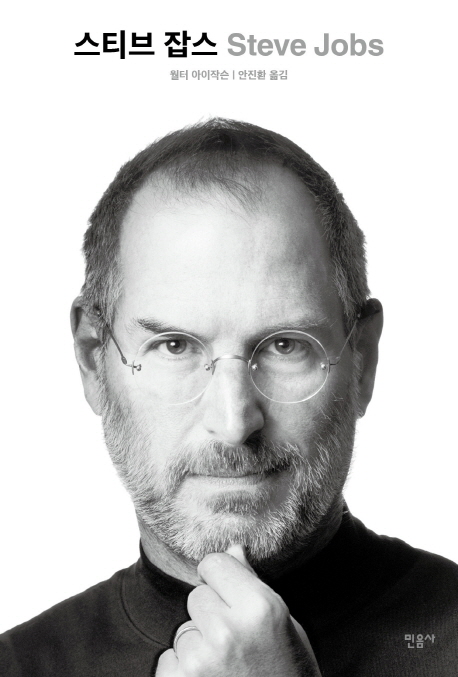
산돌고딕네오1이 적용된 스티브 잡스 자서전
본고딕(Source Han Sans) / 구글 X 어도비 X 산돌커뮤니케이션
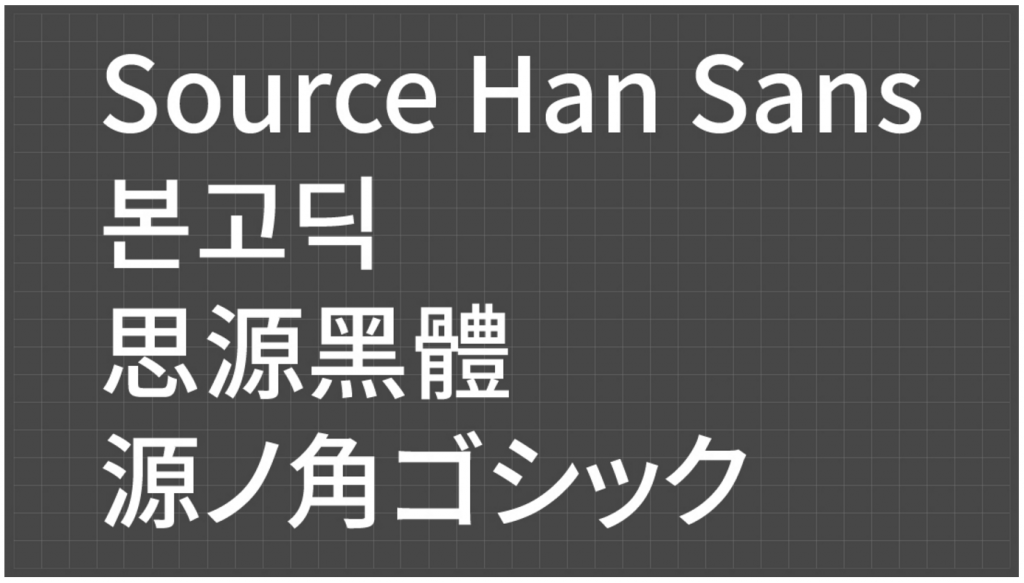
최초의 오픈소스 한중일 통합폰트, 본고딕
구글과 어도비 그리고 산돌이 협력하여 한중일 3개 국어와 라틴어를 모두 지원하는 슈퍼 폰트가 만들어졌습니다. 바로 본고딕 or 노토 산스 CJK(Noto Sans CJK)입니다. 어도비는 ‘누구나 사용 가능한 오픈 소스 서체 개발’에 지속적으로 관심을 가지고 있었고, 구글 역시 같은 뜻으로 프로젝트에 함께 했습니다. 전세계 모든 정보를 체계화해 언제 어디서 누구든 용이하게 정보에 접근하게 하는 것이 구글의 목표이기 때문입니다. 한글은 다양한 글로벌 프로젝트 경험을 보유한 산돌이 담당하였습니다.
한중일 3개국어를 완벽하게 지원하는 7종류의 굵기로 제작되었으며, 각 나라 글꼴의 특색을 살리면서도 조화롭고 일관된 느낌을 받을 수 있도록 제작하였습니다. 전체적으로 세련되고 현대적 스타일의 고딕체로 간소하고 일관된 획 두께로 표현되었으며 스마트폰 및 태블릿 같은 작은 화면의 디바이스에서도 텍스트를 보다 쉽게 읽을 수 있도록 가독성을 고려했습니다. 본고딕은 오픈소스이기 때문에 컨텐츠 제작자나 개발자, 디자이너들이 마음껏 사용할 수 있습니다. 이를 통해 보다 원활한 작업을 돕고 한층 향상된 사용자 경험을 제공할 수 있게 되었습니다.
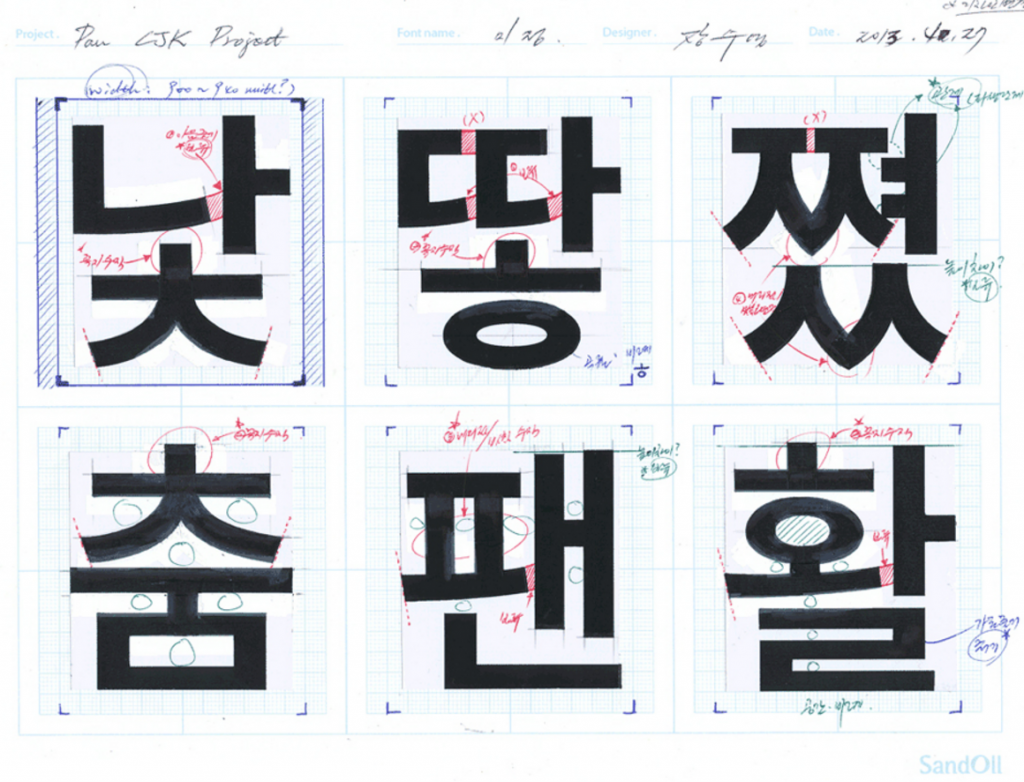
본고딕의 원도 스케치 자료
맑은고딕 / Microsoft X 산돌커뮤니케이션
모니터에 최적화된 최초의 한글 폰트, 맑은고딕
Microsoft는 Windows Vista 출시와 함께 고해상도 디스플레이 기기의 보급에 맞춰 비-라틴 언어권의 기본 폰트를 대폭 개선하기로 하였습니다. 맑은 고딕은 그 일환으로서 기존에 굴림체가 차지하고 있던 기본 UI 글꼴을 Windows Vista에서부터 대체하였습니다.
이를 위해 산돌 석금호 대표가 마이크로소프트 미국 본사를 찾아가 3일동안 경영진 및 실무자들과 차례로 토론을 벌여 설득했다는 일화는 유명합니다. 이후 2년에 걸쳐 15명의 디자이너가 개발에 투입됐으며, 마이크로소프트 본사의 엄격한 품질 검사를 모두 통과하고 2004년 Windows Vista에 탑재된 것입니다. 한글에 매뉴얼 힌팅이 적용된 최초 사례로 모니터에 최적화된 최초의 한글 폰트라 할 수 있으며, 이를 통해 화면 상에서 조형성 및 가독성을 극대화 시킬 수 있었습니다.
나눔고딕 by 네이버 X 산돌커뮤니케이션
나눔고딕은 네이버가 진행하는 ‘한글한글 아름답게’ 캠페인의 일환으로 나눔글꼴 시리즈 중 가장 먼저 출시되었습니다. 기존 굴림체에 현대적인 감각을 적용한 새로운 느낌의 고딕체로 부드러운 인상이 특징입니다.
모양도 깔끔하고 가독성도 좋아서 많은 사람들의 사랑을 받고 있는 국민폰트이기도 합니다. 네이버의 기본 폰트는 물론, 안드로이드나 우분투, 크롬 OS 등의 기본 한글폰트로 채택될만큼 사용성을 인정받았으며 칸 국제광고제에서 실버라이온스상을 수상할만큼 타이포브랜딩을 통한 마케팅 효과를 톡톡히 거두었습니다.
유앤아이(Youandi) / 현대카드 X 산돌커뮤니케이션
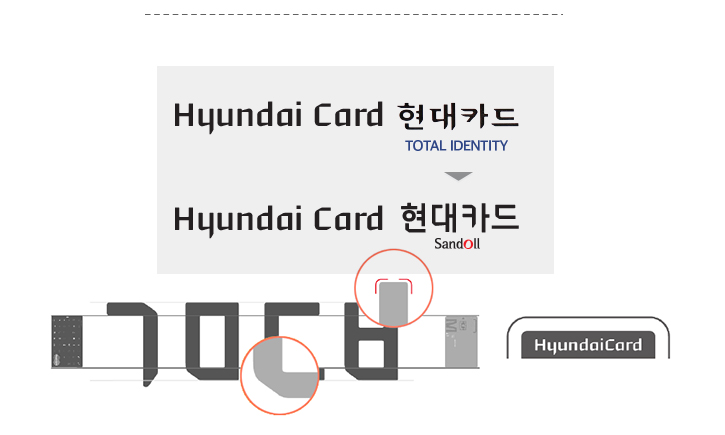
타이포브랜딩 대표적인 성공사례, 현대카드 전용서체
현대카드는 2003년 기업의 브랜딩을 위해 CI 작업과 함께 자신들의 전용서체를 개발하게 되었습니다. 네덜란드의 디자인회사 토털 아이덴티티가 영문 폰트를 개발하였고, 이를 토대로 산돌에서 한글 작업을 진행했습니다. 신용카드의 형태와 비율, 각도를 그래픽 모티브로 했으며, 거기에 더해 세련미를 극대화하고자 했습니다.
카드 모양을 본따 글자를 만들면서 모서리 부분의 각을 제거함으로써 날렵하면서도 디지털에 어울리는 디자인이 나오게 되었습니다. 이후 현대카드는 회사 내부에 전담 디자인팀을 신설해 서체를 포함한 기업의 아이덴티티 유지와 구축 작업을 진행하고 있으며 이를 통해 가장 강력한 브랜드를 지닌 신용카드로 거듭날 수 있었습니다.
올레체 네오 / KT X 산돌커뮤니케이션
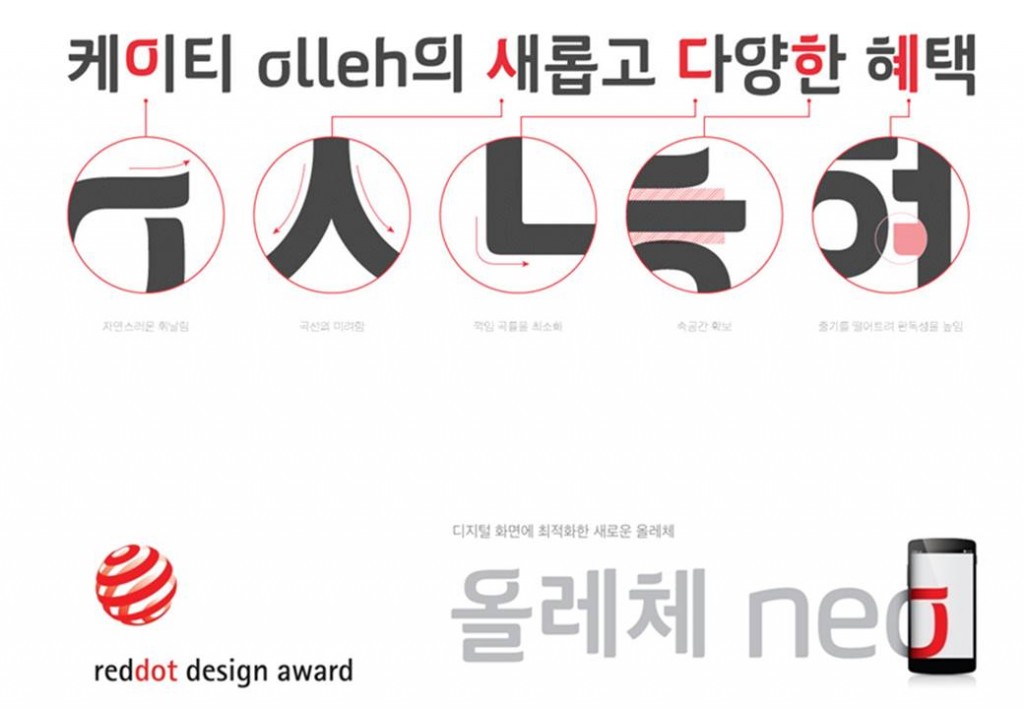
성공적인 디자인 리뉴얼로 2014 Red dot design award 수상
KT는 전용서체인 올레체를 개발하면서 효과적인 타이포 브랜딩을 진행해 왔습니다. 서체의 독특한 형태를 통해 KT의 아이덴티티를 대중들에게 인식시키는데는 성공했고, 사람들은 휘날리는 글자 끝만 보아도 ‘KT 올레’를 연상시킬 수 있었습니다.
하지만 폰트의 사용성에 대한 문제가 대두되기 시작하면서, ‘올레체 리뉴얼 프로젝트’가 시작되었습니다. 보다 완성도 있는 서체로 기업의 이미지를 업그레이드하고, 시대 흐름에 발맞춰 모바일 디스플레이에도 최적화하는 것이 주 목적이었습니다. 산돌과 함께 한 이 리뉴얼 과정을 통해서 기능적, 조형적인 면에서 한단계 더 진화한 ‘올레체 네오’가 탄생했고, 성공적인 디자인 리뉴얼로 사용성은 물론 2014 Red dot design award에서 상을 받기도 하였습니다.
배달의민족 한나는열한살, 도현체 / 우아한형제들 X 산돌커뮤니케이션
이제는 출판, 방송, 광고 업계에서 두루 사용하는 국민폰트
배달의민족이 폰트를 만든다? 언뜻 들어선 믿기 어려운 일이지만 사실입니다. 대표적인 배달앱 ‘배달의민족’을 서비스하는 ‘우아한형제들’에서 진행하는 우아한 나눔 프로젝트, 그 중 하나가 배달의민족 글꼴이며 심지어 무료로 배포됩니다.
70~80년대 간판의 키치하고 복고적인 느낌을 현대적으로 재해석한 것이 배달의민족 글꼴의 특징이라 할 수 있으며, 누구나 제약없이 쓸 수 있다는 점 때문에 이제는 출판, 방송, 광고 업계에서 두루 사용하는 국민폰트가 되었습니다. 여기에는 산돌도 함께 하였는데, 우아한 형제들과 산돌의 협업으로 폰트의 완성도를 크게 높일 수 있었습니다.
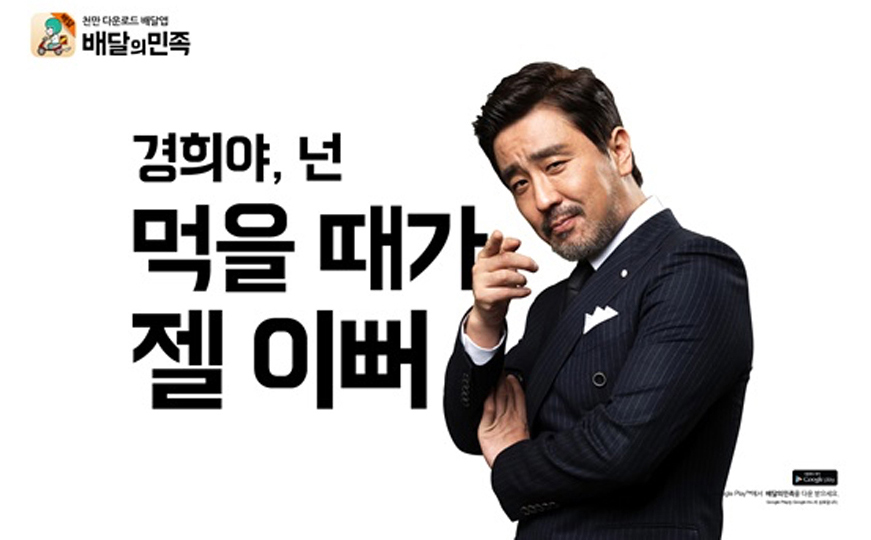
클래시 오브 클랜 전용서체 / 슈퍼셀 X 산돌커뮤니케이션
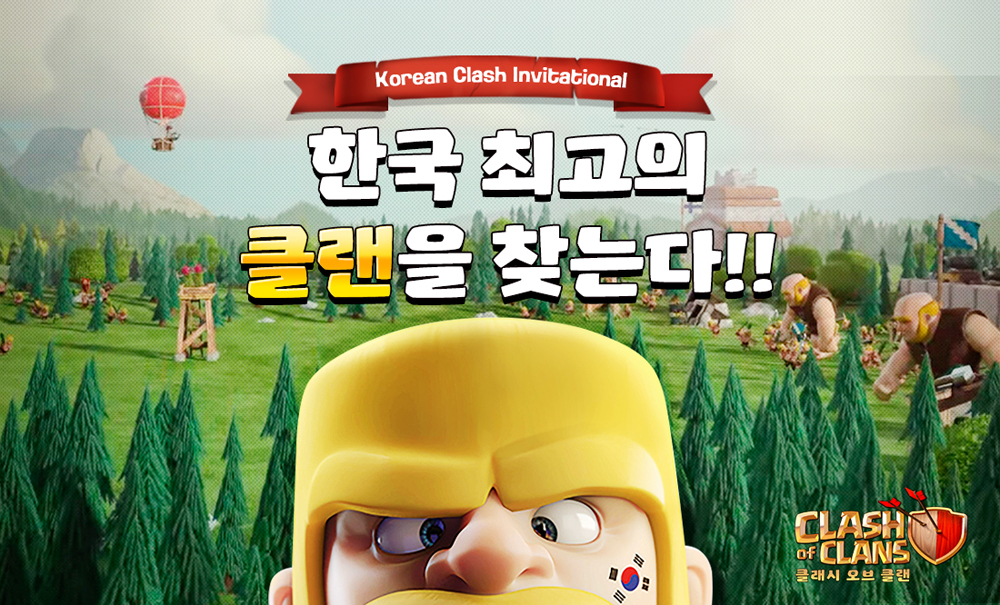
자신들의 아이덴티티에 맞는 전용폰트를 개발한 슈퍼셀
클래시 오브 클랜의 전세계적인 슈퍼 히트로 모바일 게임업계를 평정한 슈퍼셀(SUPERCELL). 슈퍼셀은 핀란드의 게임회사로 클래시 오브 클랜 뿐만 아니라 붐비치, 헤이데이 등의 게임을 통해 자신들만의 색깔을 확실히 구축해나가고 있으며, 그들의 대표작 클래시 오브 클랜은 출시한 이래 인기순위 상위권을 놓치지 않고 세계 135개국 유저들이 함께 즐기는 게임으로 발돋움하였습니다.
이들은 브랜딩을 위해 영문전용서체를 개발하여 효과적으로 사용하고 있었으나, 한글 서체는 따로 가지고 있지 않아 게임에서 뿐만 아니라 마케팅에서도 게임의 매력을 잘 살리지 못하는 한계가 있었고, 이를 극복하기 위해 클래시 오브 클랜과 잘 어울리는 한글 전용서체 제작을 산돌에 의뢰하여 프로젝트가 진행되었습니다. 이를 통해 몰입감 있는 게임경험을 제공하고 효과적인 마케팅을 펼칠 수 있었습니다.
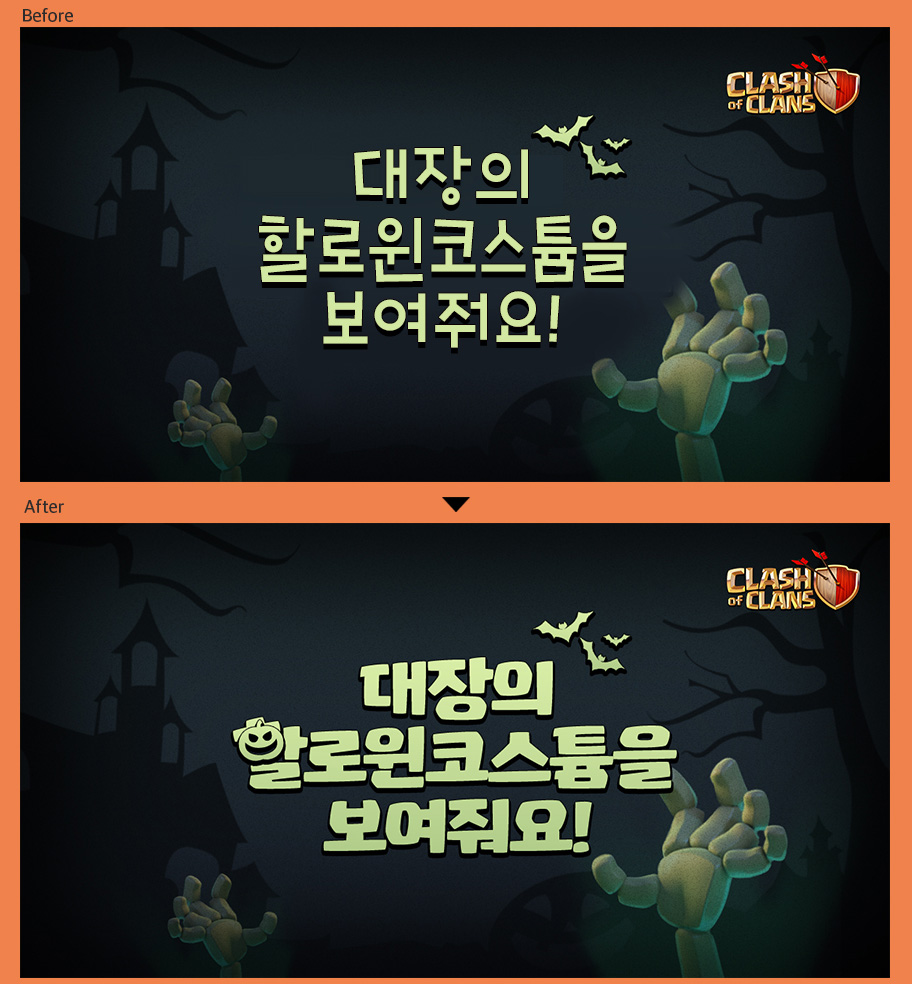
산돌 국대떡볶이 / 국대떡볶이 X 산돌커뮤니케이션
대표적인 프랜차이즈 브랜드 국대떡볶이의 리뉴얼과 함께 시작된 프로젝트입니다. 국대떡볶이의 로고로 사용하는 것은 물론 다양한 분야에 폭 넓게 사용 할 수 있도록 다양한 부분을 고려하여 제작되었습니다.
기존 국대떡볶이의 로고는 작게 썼을 경우 가독성이 떨어지고 덩어리감이 약하여 선명한 인상을 주기 어렵다는 문제점이 있었고, 이러한 문제점을 해결하고 폰트로서 사용할 경우 로고타입의 느낌이 잘 살아 날 수 있도록 국대떡볶이만의 개성과 특징을 살리는데 주안점을 두었습니다. 제작된 폰트는 누구나 사용할 수 있도록 무료로 배포되어 많은 사람들에게 사랑받는 국민폰트가 되었습니다.